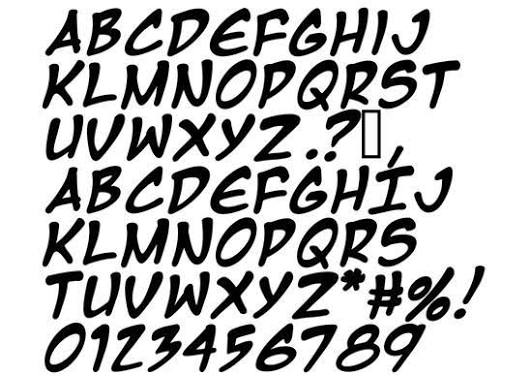
Nhiều designer khi sử dụng font Manga thường gặp lỗi thiếu dấu tiếng Việt hoặc các hiệu ứng SFX (Sound Effects) bị mất chi tiết khi in trên bao bì và quà tặng dành cho trẻ em. Những lỗi hiển thị này khiến thiết kế mất đi sự sinh động, làm giảm sức hút của sản phẩm trong quá trình tiếp cận khách hàng.
Font Manga là gì?
Font Manga là nhóm các phông chữ được thiết kế dựa trên phong cách trình bày của truyện tranh Nhật Bản. Đặc trưng của dòng phông này là các đường nét giàu tính biểu cảm, từ những kiểu chữ bo tròn đáng yêu dành cho lời thoại nhân vật đến những kiểu chữ góc cạnh, mạnh mẽ dành cho các hiệu ứng âm thanh (Font sfx manga Việt hóa). Trong ngành thiết kế bao bì, font Manga giúp tạo nên sự vui tươi, phá cách và đầy năng lượng, đặc biệt hiệu quả cho các sản phẩm snacks, đồ chơi hoặc văn phòng phẩm trẻ em.
Một trong những bộ phông nổi tiếng trong nhóm này là Font Manga 6 Việt hóa, được ưa chuộng bởi độ rõ nét và tính ứng dụng cao. Tuy nhiên, phông chữ phong cách truyện tranh thường có cấu trúc nét phức tạp, dễ gặp lỗi khi gõ các dấu thanh tiếng Việt. Bộ sưu tập tại In Viva đã được tinh chỉnh hệ thống dấu thanh hài hòa với các nét chữ nghệ thuật, giúp bản thiết kế của bạn luôn sống động và thẩm mỹ trên mọi chất liệu từ túi giấy đến ly sứ.
- Tối ưu đường Path cho gia công bế nổi: Khi sử dụng font Manga làm logo hoặc họa tiết trên hộp quà, file vector cần được xử lý các điểm neo và đường cong phức tạp. Việc tối ưu path giúp khuôn bế tái hiện rõ hình dạng chữ, hạn chế ảnh hưởng đến bề mặt giấy trong quá trình gia công.
- Kiểm tra vùng chồng màu (Overprint): Font Manga thường sử dụng nhiều lớp màu, viền chữ và hiệu ứng bóng. Designer nên kiểm tra thông số màu trước khi in để hạn chế hiện tượng lệch viền hoặc khoảng trắng giữa các lớp mực.
- Lựa chọn chất liệu in phù hợp: Font Manga thường phù hợp với các chất liệu có khả năng thể hiện màu sắc rõ như giấy Couche, giấy Ivory cán màng, decal hoặc sản phẩm in UV. Việc lựa chọn chất liệu phù hợp giúp giữ được hiệu ứng màu sắc của thiết kế.